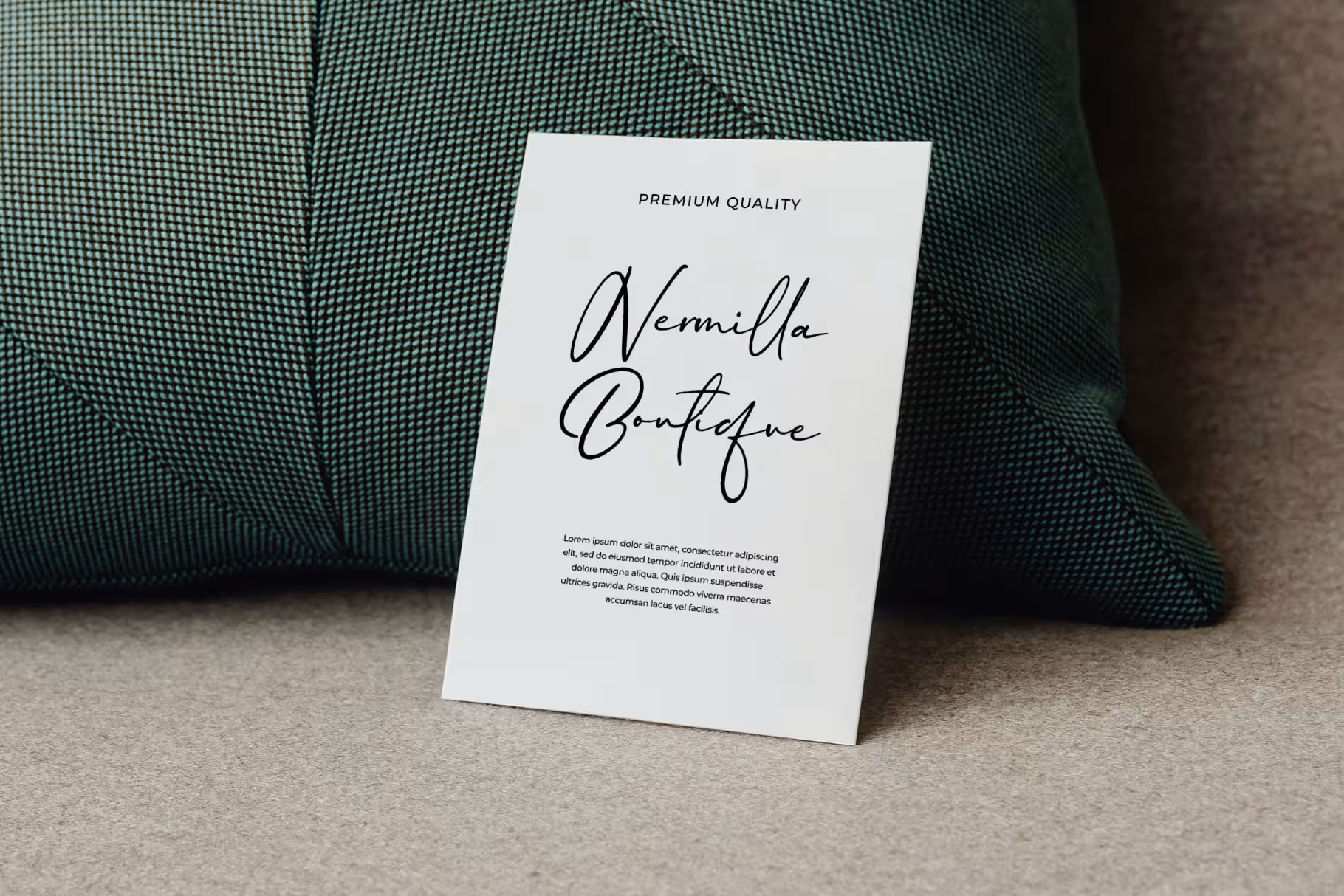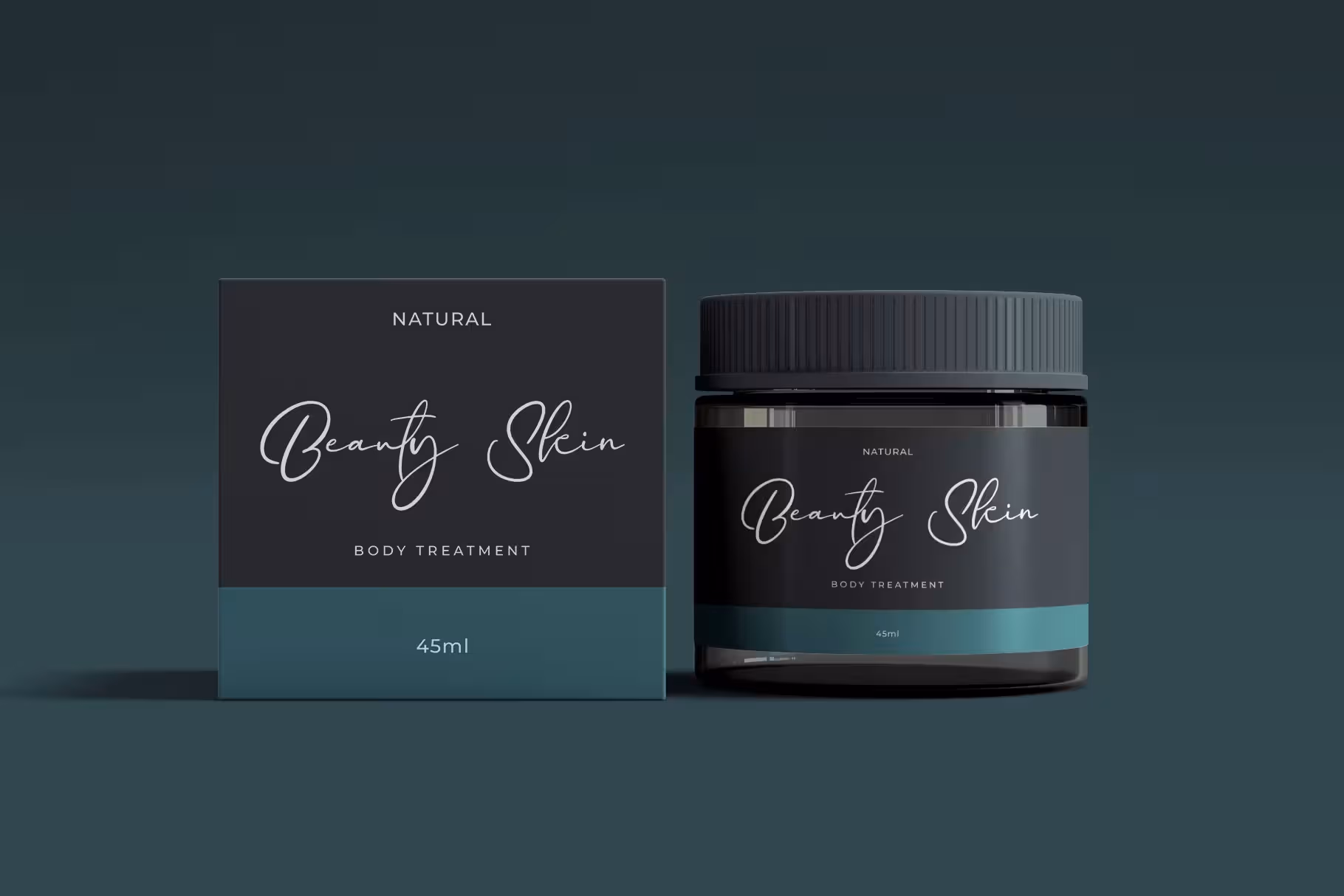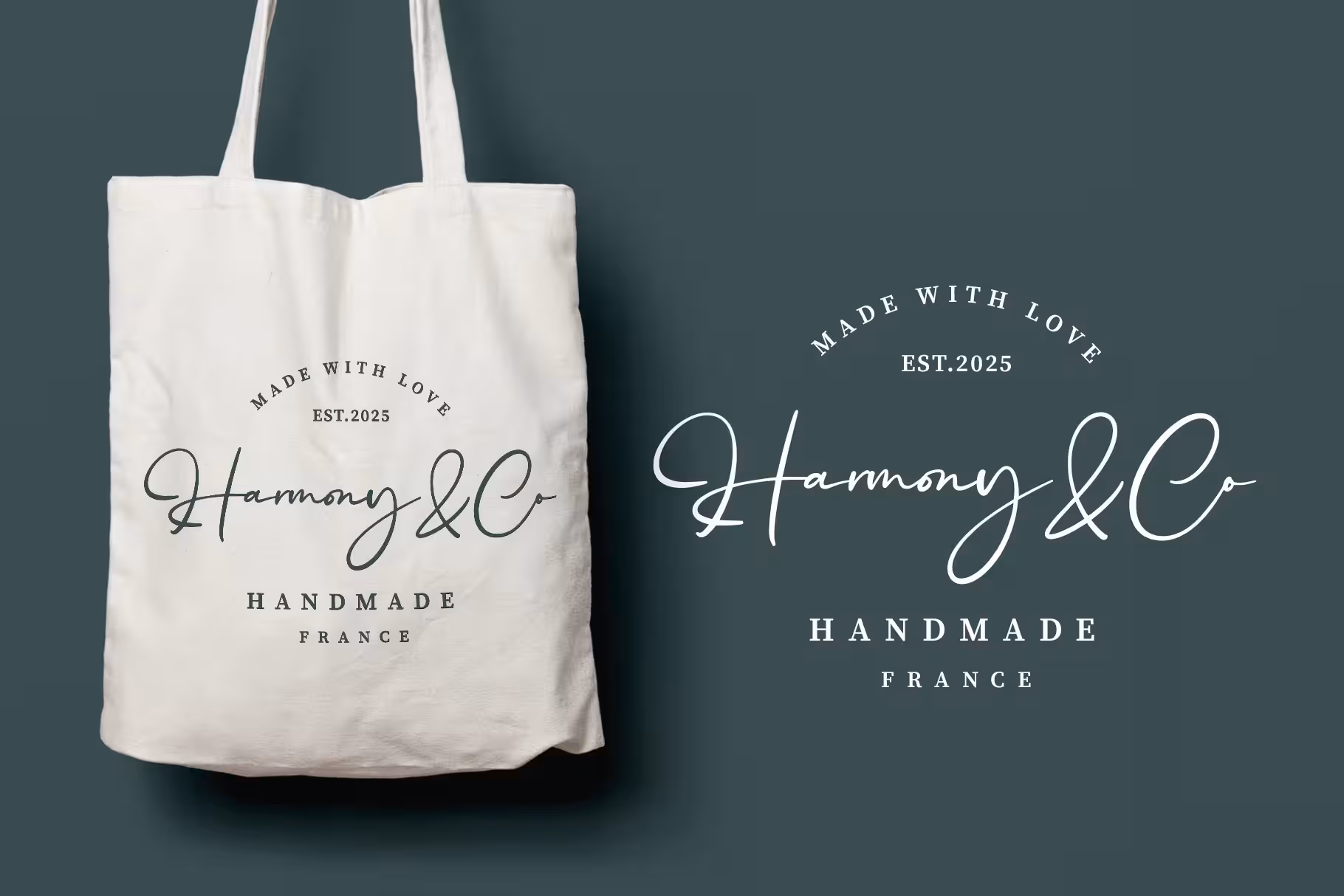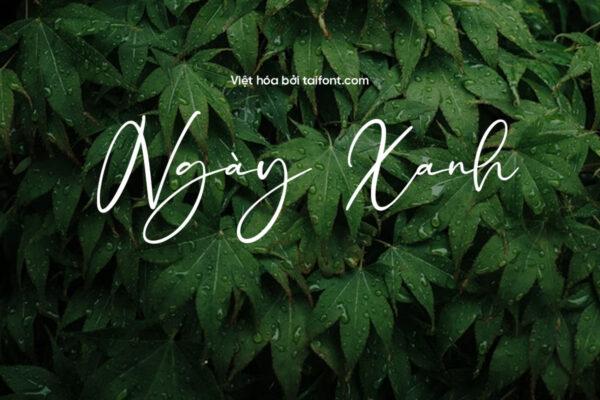
Giới thiệu về Font TF Muselint Việt hóa
TF Muselint Việt hóa là một font chữ viết tay (script font) nổi bật với những đường nét phóng khoáng, tự nhiên và đầy thú vị, mang đến vẻ đẹp vừa tinh tế vừa cá tính. Font này gợi cảm giác như một chữ ký được viết nhanh, có hồn, tạo nên sự độc đáo và riêng biệt cho mọi thiết kế. Sự kết hợp giữa nét thanh thoát và sự ngẫu hứng trong từng ký tự làm cho Muselint trở nên rất cuốn hút.
Với sự duyên dáng và tính thẩm mỹ cao, Muselint là lựa chọn lý tưởng cho các thiết kế muốn truyền tải sự tinh tế, cá nhân hóa và một chút nghệ thuật:
- Thiết kế thời trang: Hoàn hảo cho các nhãn mác quần áo, tem nhãn phụ kiện, hoặc các chi tiết nhỏ trong lookbook. Font này giúp truyền tải vẻ đẹp thanh lịch, độc đáo và dấu ấn của nhà thiết kế.
- In ấn túi vải (tote bag): Lý tưởng để in các câu trích dẫn, slogan, hoặc tên thương hiệu lên túi vải. Nét viết tay của Muselint sẽ làm cho chiếc túi trở nên cá tính, phong cách và thu hút sự chú ý.
- Thiết kế mỹ phẩm: Phù hợp để sử dụng trên bao bì sản phẩm, nhãn mác hoặc các ấn phẩm quảng cáo mỹ phẩm. Font này giúp truyền tải sự tinh tế, độc đáo và vẻ đẹp tự nhiên của sản phẩm, thu hút đối tượng khách hàng tìm kiếm sự khác biệt.
Với TF Muselint Việt hóa, bạn có thể dễ dàng thổi hồn nghệ thuật, sự tinh tế và cá tính vào các thiết kế, tạo ra những sản phẩm không chỉ đẹp mắt mà còn đầy cảm xúc và sức hút đặc biệt.
Font Việt hóa TF Muselint